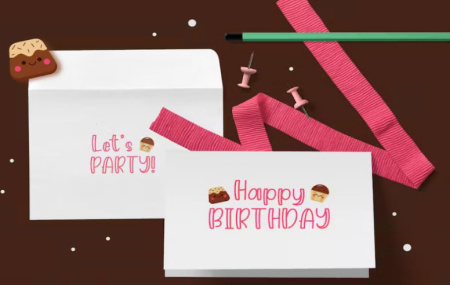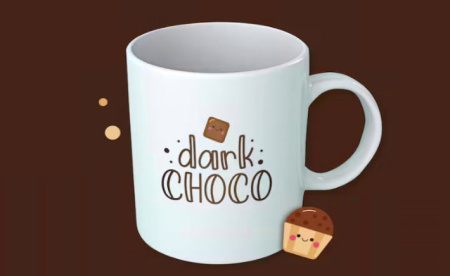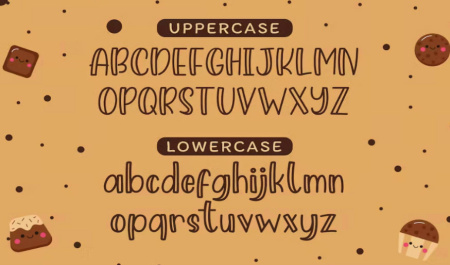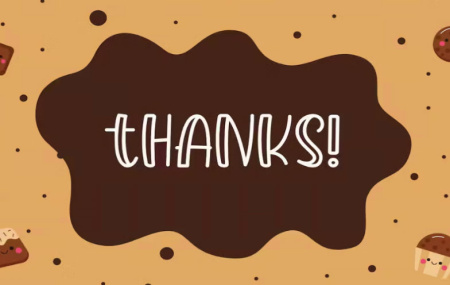
دانلود فونت انگلیسی بامزه Home made choco
دانلود فونت انگلیسی Home made choco از جی اف ایکس دانلود. فونت‌های صفحه‌ نمایش بازیگوش و بامزه است. تک تک حروف با دقت ساخته شده‌اند تا متن شما زیبا به نظر برسد. با سبک منحصر به فرد مدرن، این فونت انگلیسی برای بسیاری از پروژه های مختلف مانند نقل قول، سربرگ وبلاگ، پوستر، عروسی، برندسازی، لوگو، مد، پوشاک، نامه، دعوت نامه، لوازم التحریر و غیره عالی خواهد بود.